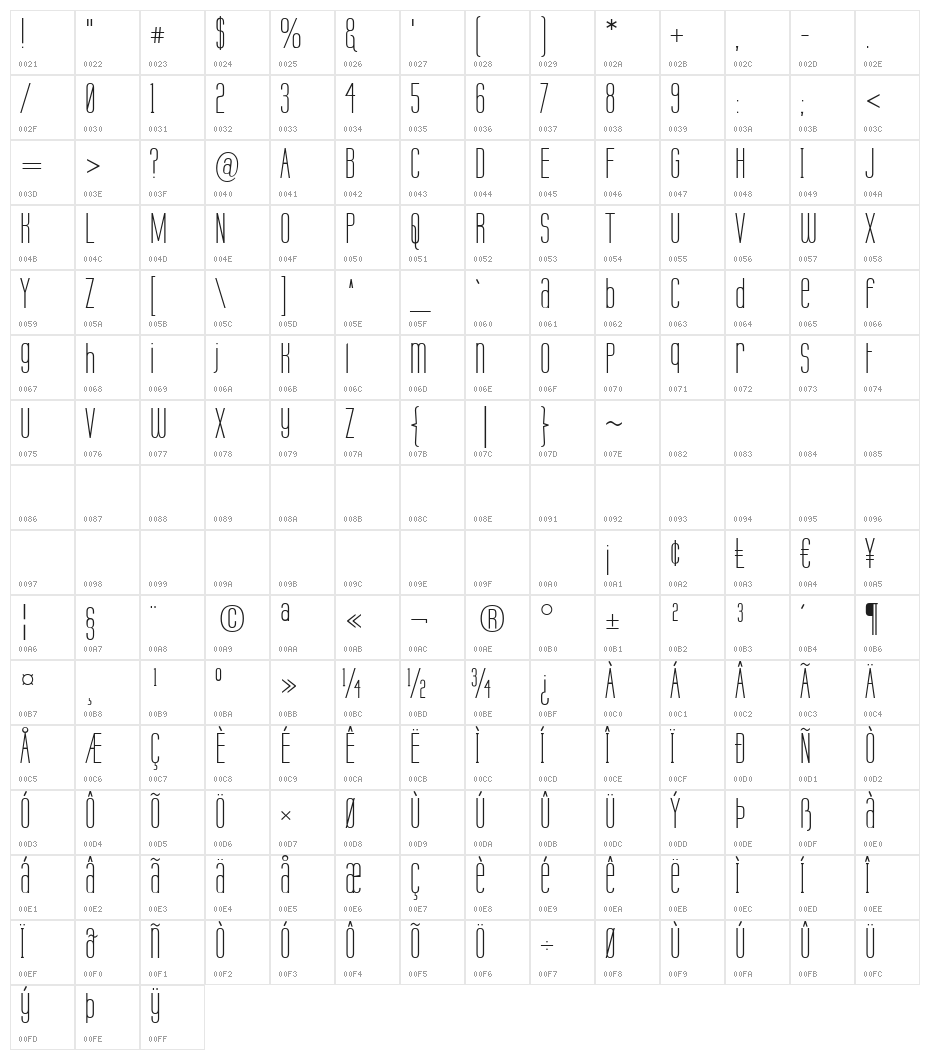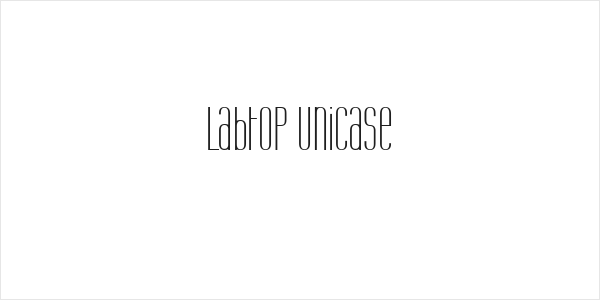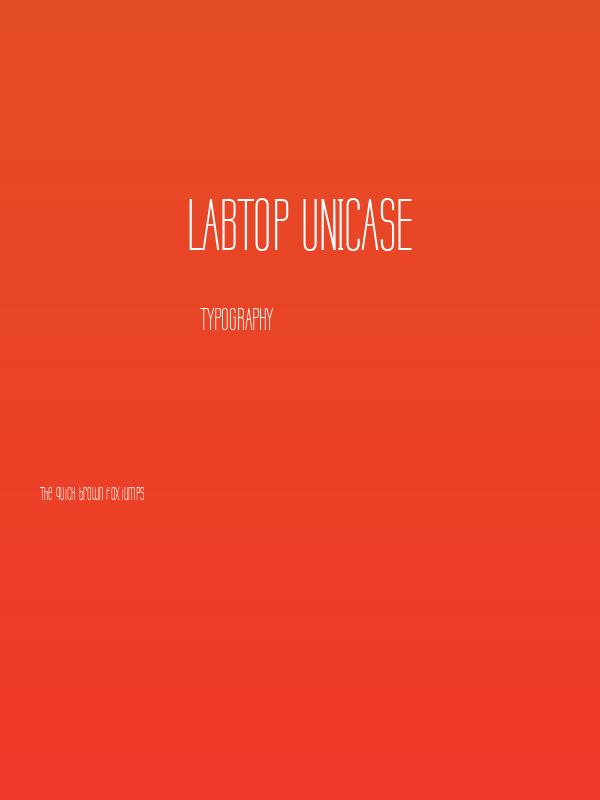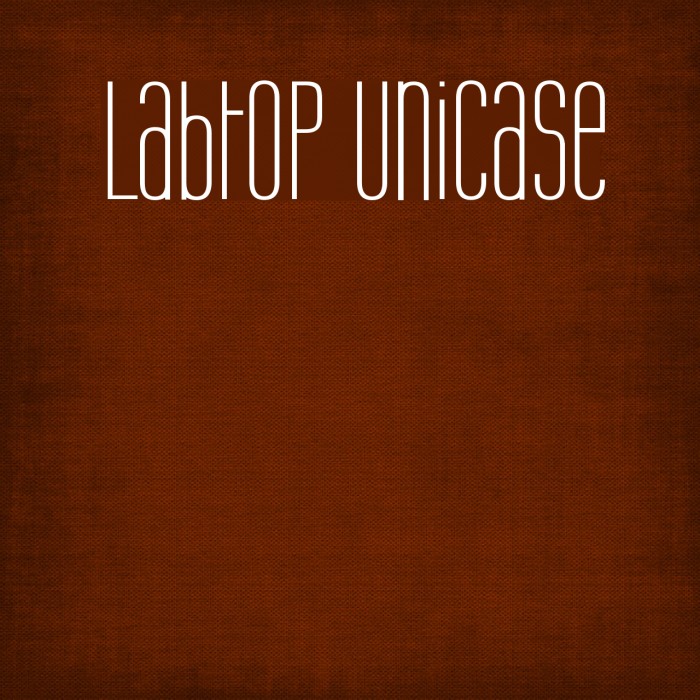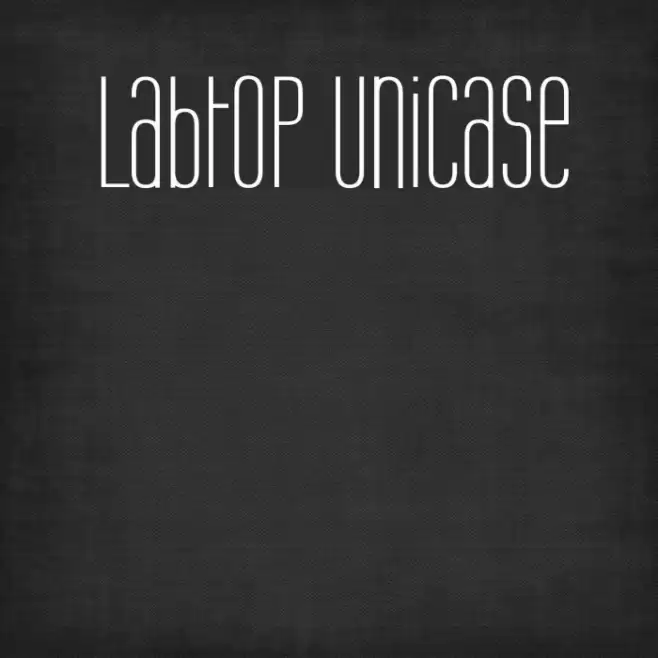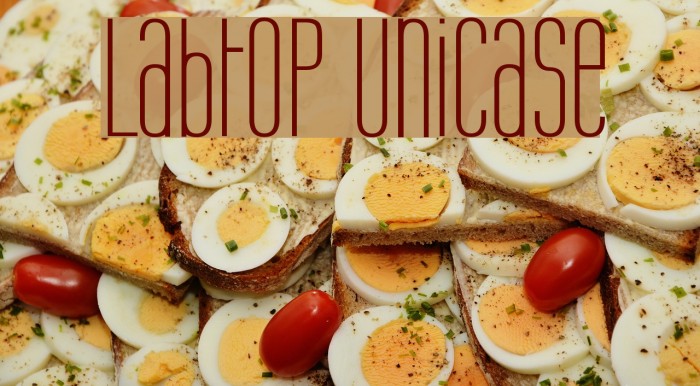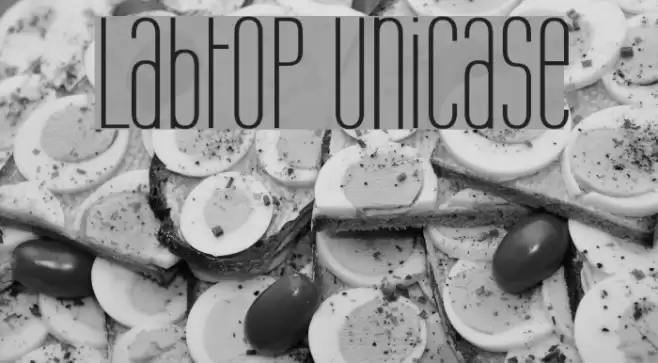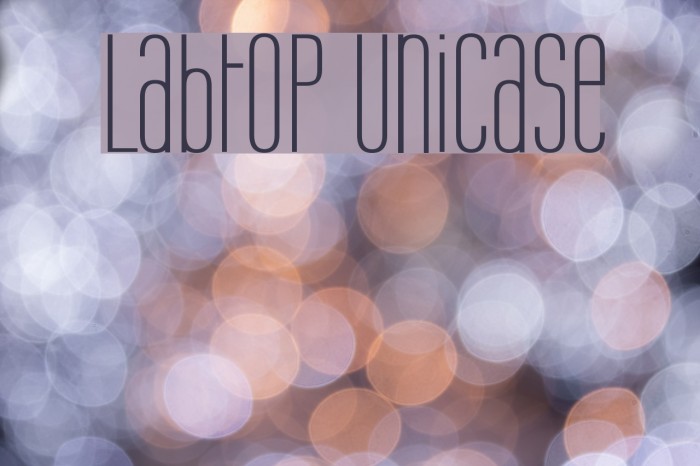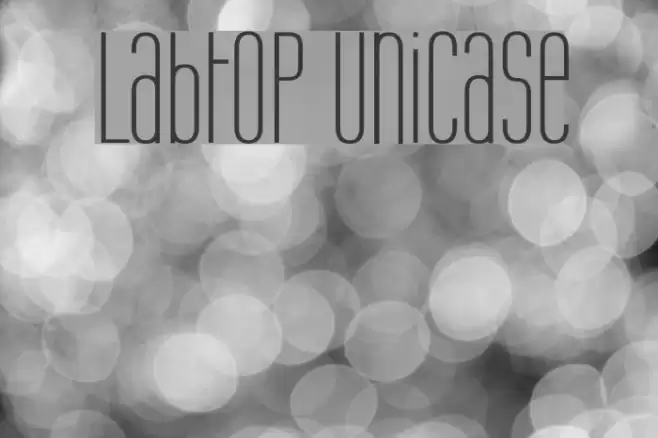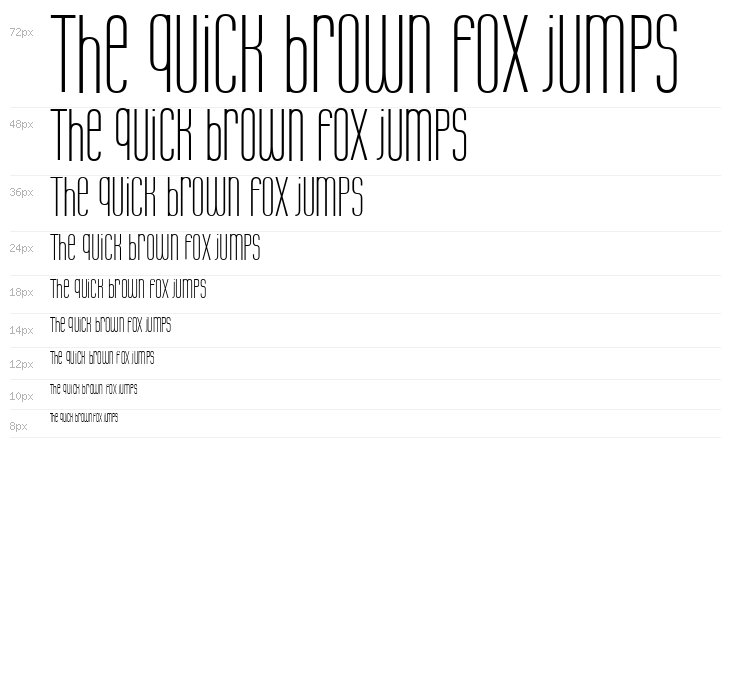
Labtop Unicase Font
Fonts by Apostrophic Lab
| Progetti proposti | Ideal for fashion magazines, modern branding, minimalist posters, and digital interfaces. |